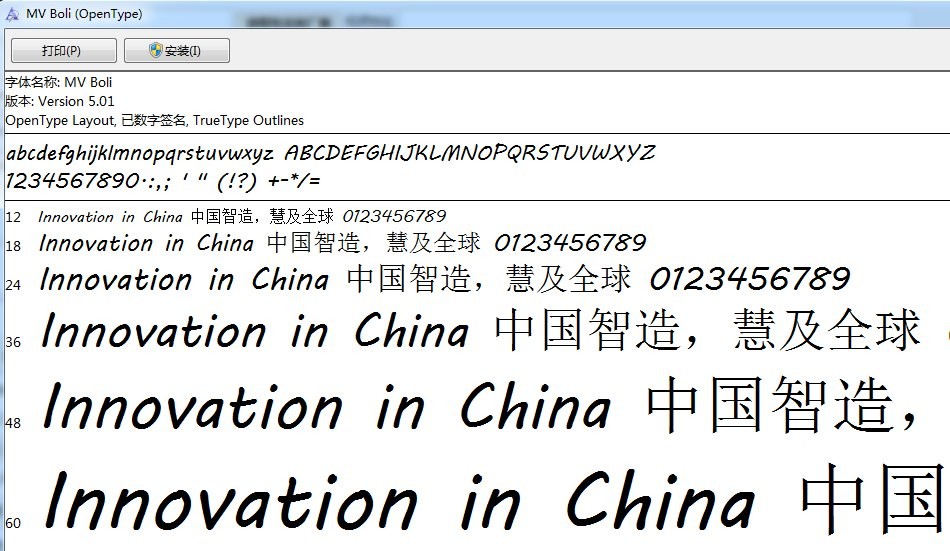
mv boli字體風格很獨特,整個給人一種比較輕松的視覺效果,不管是用于海報、畫冊還是其他封面設(shè)計都很合適,適用范圍非常廣泛,而且安裝包超小,安裝完成之后就能在電腦上使用,也可以將其添加到ps中,對于做設(shè)計的用戶來說很有幫助,
mv boli是一款很受歡迎的英文字體,字形看起來細細的,看上去比較秀氣,并且有一種活潑靈動的感覺。